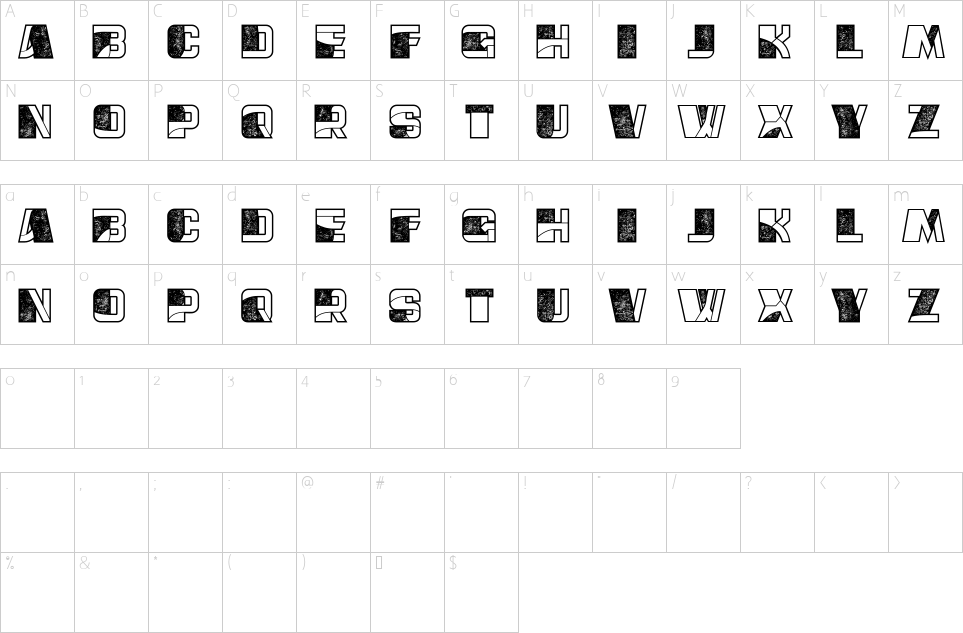
A Argentina Font é uma elegante e sofisticada fonte gráfica que oferece um toque latino para suas criações digitais. Desenhada por Vladimir Nikolic, esta font é uma excelente escolha para quem busca um visual atraente e moderno. Download da Argentina Font para Windows e Mac, esta font é perfeita para projetos profissionais e pessoais. Com sua versão gratuita, você pode experimentar o charme único da Argentina Font em seus projetos digitais, sem comprometer o design. Embora não sejam muitos os downloads, o fato de a font ser gratuita e altamente demandada sugere que ela tem um design único e de qualidade. Por isso, é uma fonte que vale a pena explorar para aqueles que procuram algo novo e especial para suas criações.